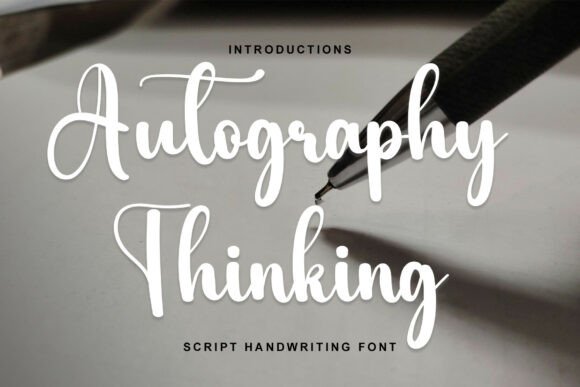
Autography Thinking
適切なデザイン要素を見つけるのは難しい場合がありますが、Autography Thinkingは作品を即座に引き立てる優れたコレクションを提供します。
POD(オンデマンド印刷)製品、結婚式の招待状、またはソーシャルメディアのグラフィックを作成している場合でも、Autography Thinkingは理想的です。